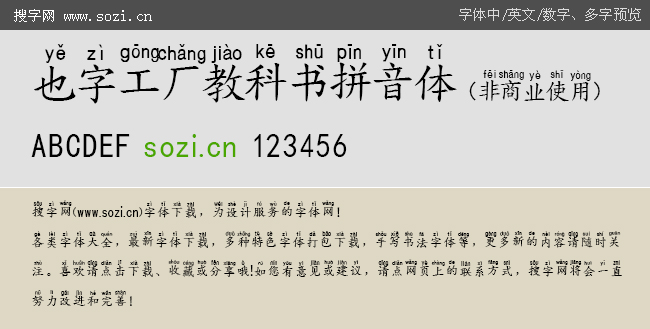
也字工廠教科書(shū)拼音體
搜字網(wǎng)給大家提供一款也字工廠教科書(shū)拼音體(非商業(yè)使用)中文字體下載,也字工廠教科書(shū)拼音體是一款楷體字體,字體方正,字形簡(jiǎn)潔大方。上部配有漢語(yǔ)拼音。具有很好的視覺(jué)效果。適合應(yīng)用于藝術(shù)設(shè)計(jì)、平面宣傳設(shè)計(jì)、網(wǎng)頁(yè)設(shè)計(jì)、海報(bào)設(shè)計(jì)等應(yīng)用(此字體為個(gè)人非商用版,商用可以聯(lián)系:官方網(wǎng)址:https://yefont.com/home,聯(lián)系方式:13798980448)。